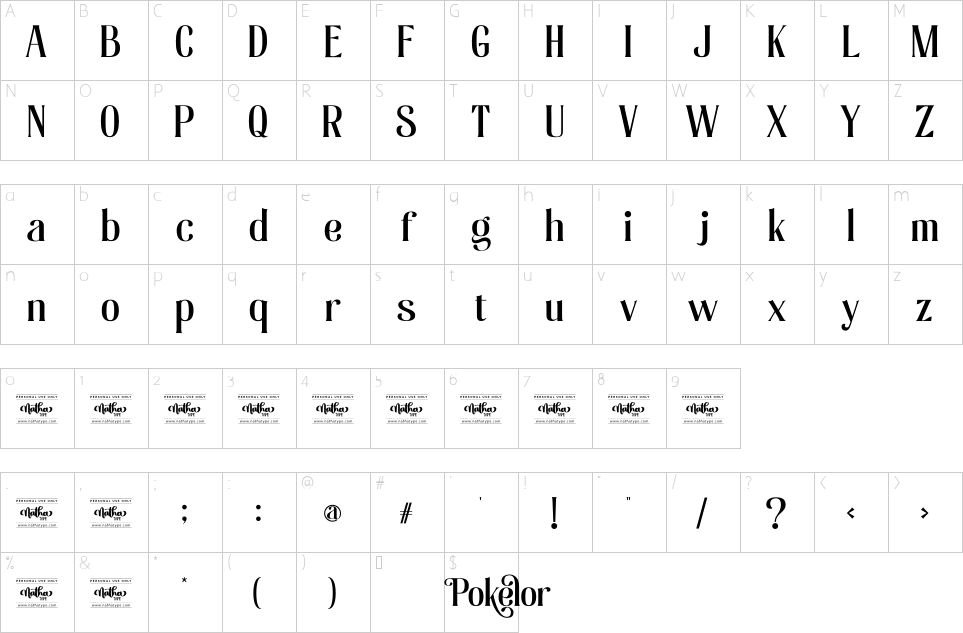
A fonte Pokelor é um presente para designers amantes de uma estética natural e envolvente. Feita pelo designer Natha Type, Pokelor foi projetada para dar um toque único em qualquer projeto. Suas formas delicadas e linhas fluidas transmitem harmonia e elegância, fazendo dela uma escolha ideal para desenhos gráficos, e-books e design de marca. Com uma variedade de pesos e estilos, Pokelor é flexível o suficiente para adicionar profundidade a qualquer página de site ou livro impresso. Com seu download facilmente disponível para Windows e Mac, é fácil para designers de todos os níveis se envolverem com Pokelor, potencializando a paleta de sua criação visual.